無料でダウンロード出来ちゃうフォントってたくさんありますよね。
今回はその中でも無料で使えちゃうユニークなフォントサイトを紹介したいと思います。
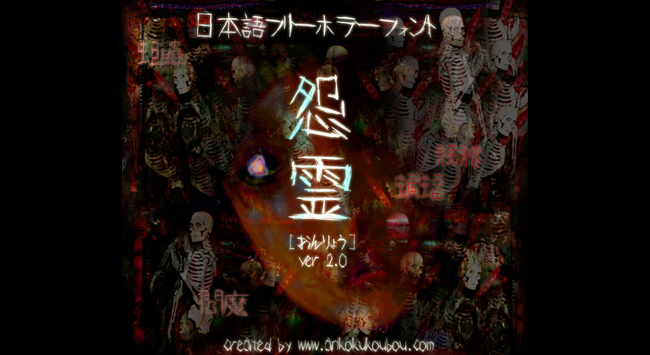
怖いフォントがいろいろありますが怨霊フォントは私のお気に入りです。
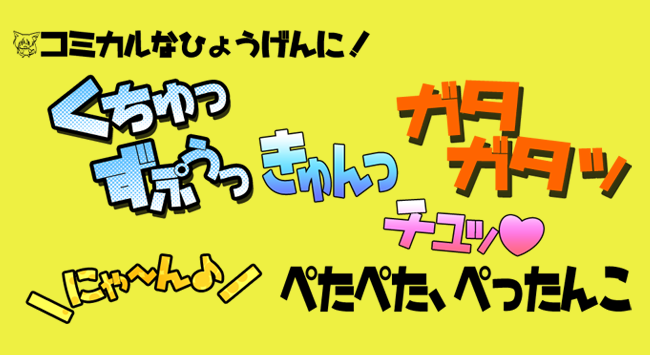
インパクトがある可愛いフォントです。
記号も種類が多くて使えそうですね。
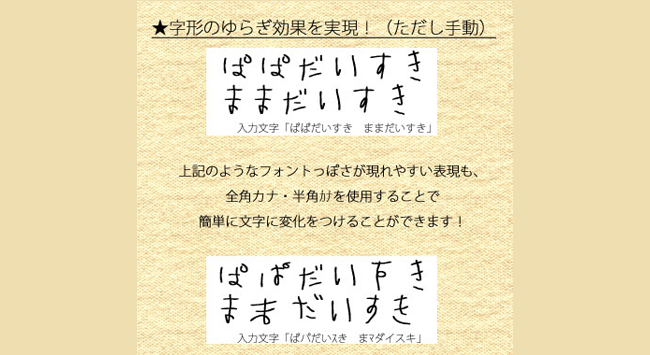
幼女が書いたような文字のフォントです。
でもちょっとホラーにも見えたりするのはホラー脱出ゲームのやり過ぎでしょうか。
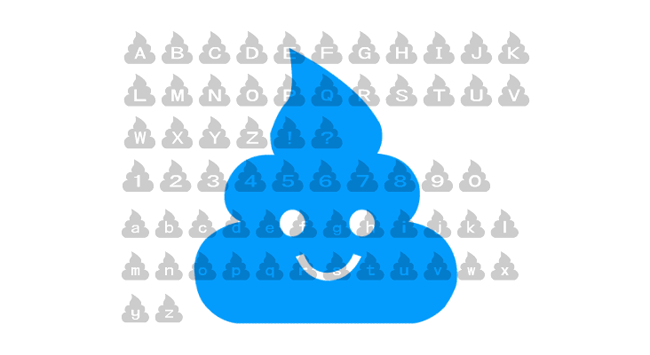
可愛いう○ちのフォントです。
欧文のみで使う場面があるかは不明ですが面白いです!
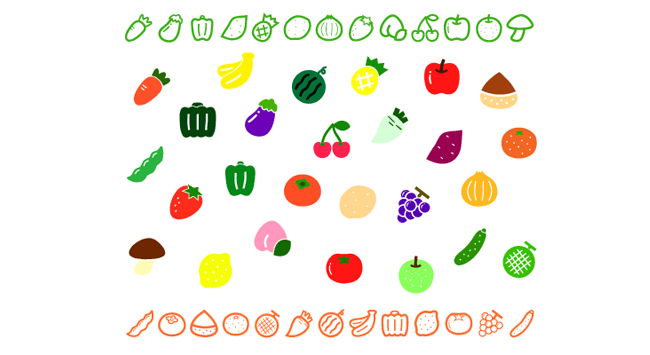
もはや文字ではないですが野菜や果物の種類も多くて
絵文字感覚で使えそうですね。
探してみると面白いフォントを見つけることが出来ました。
どれも個性的なフォントで文字を打つのが楽しくなります。
思わず使う機会はともあれインストールしたくなりますね!